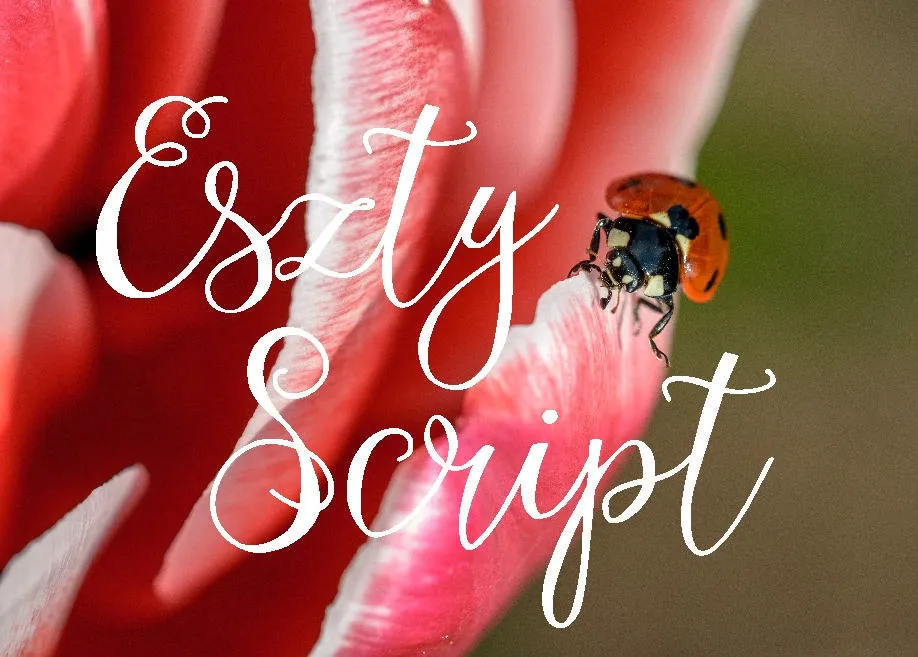
Descubra a versatilidade completa da Eszty Script Font. Introduzida pelo designer Eva Barabasne Olasz, essa tipografia tem sido um recurso essencial para projetos diversos. Com seu conjunto completo de caracteres, incluindo maiúsculas e minúsculas, números, pontuações e símbolos monetários, a Eszty Script está perfeitamente equipada para uma vasta gama de aplicações. Suas linhas elegantes se destacam perfeitamente em projetos como identidades corporativas, embalagens de produtos, cartões de casamento e design de interiores. Além disso, ela é ideal como um overlay de texto sobre qualquer imagem de fundo, oferecendo uma personalização única para seus projetos digitais. Essa Eszty Script é uma ótima adição ao seu arsenal de recursos gráficos, proporcionando criatividade e variedade sem esforço.